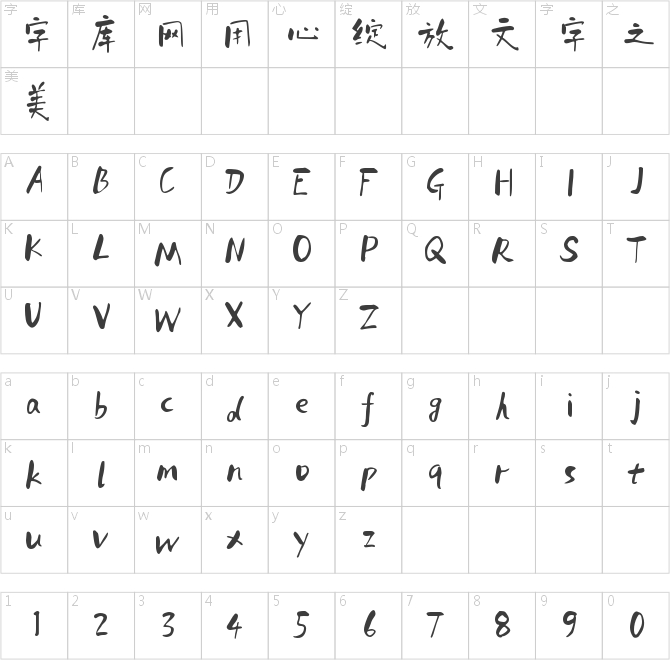
Aa人間蹉跎 詳情頁(yè)
Aa人間蹉跎字體下載
Aa人間蹉跎字體字庫(kù)是一款讓人賞心悅目、百看不厭的中文字體,適合各類廣告和產(chǎn)品包裝設(shè)計(jì)應(yīng)用,字體大小4.79MB,格式為ttf字體,上傳用戶是Aa字庫(kù),作者/版權(quán)方為Aa字庫(kù)